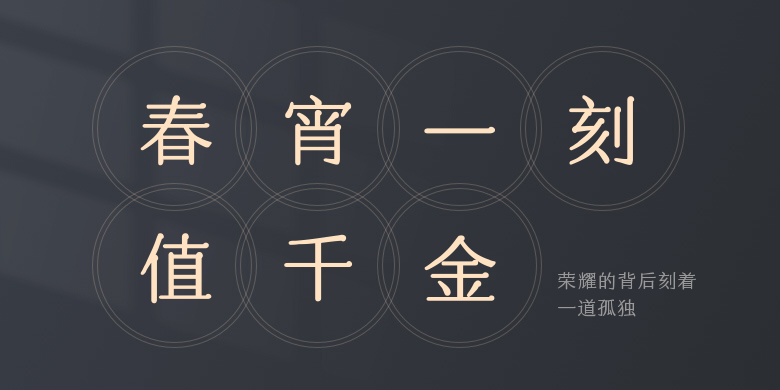
荣耀的背后刻着一道孤独
荣耀的背后刻着一道孤独,这款字体结构工整、笔画清晰,兼顾美观与易读性,适用于标题、正文、海报、包装、LOGO 等多种场景。字形优雅稳定,风格百搭耐看,适配日常排版与创意设计,让文字呈现更舒适、更具质感。荣耀的背后刻着一道孤独一笔一画,皆是细节,以均衡的比例、流畅的线条打造舒适视觉体验,字形端正大气,风格简约现代。无论是商业设计、品牌宣传还是日常排版,都能轻松驾驭,让文字更有格调与力量。荣耀的背后刻着一道孤独字体下载。